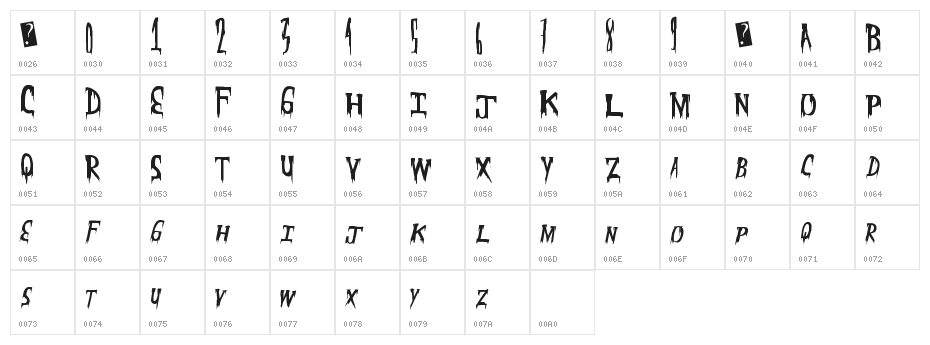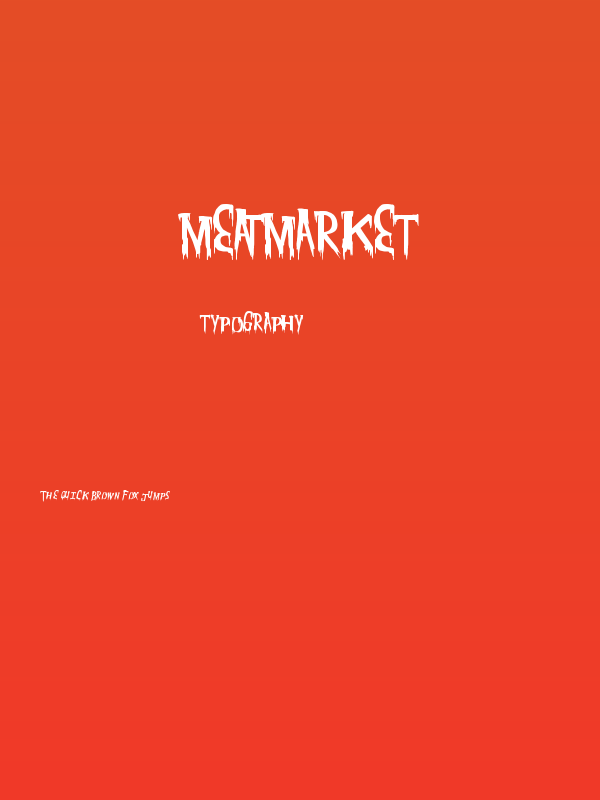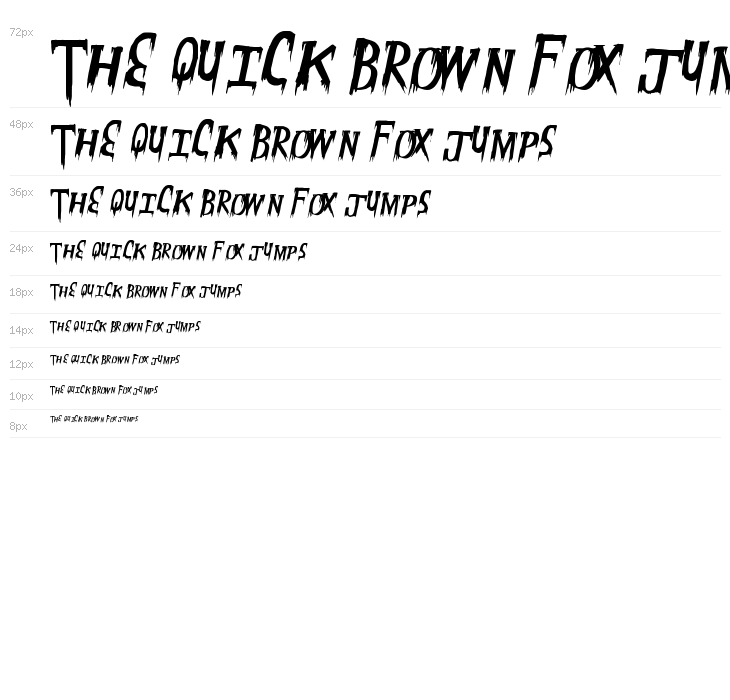
MeatMarket Font
| Caso d'uso | Headlines, Posters, Themed Events |
| Progetti proposti | Ideal for horror-themed posters, Halloween invitations, edgy album covers, or any project requiring a bold, unsettling aesthetic. |